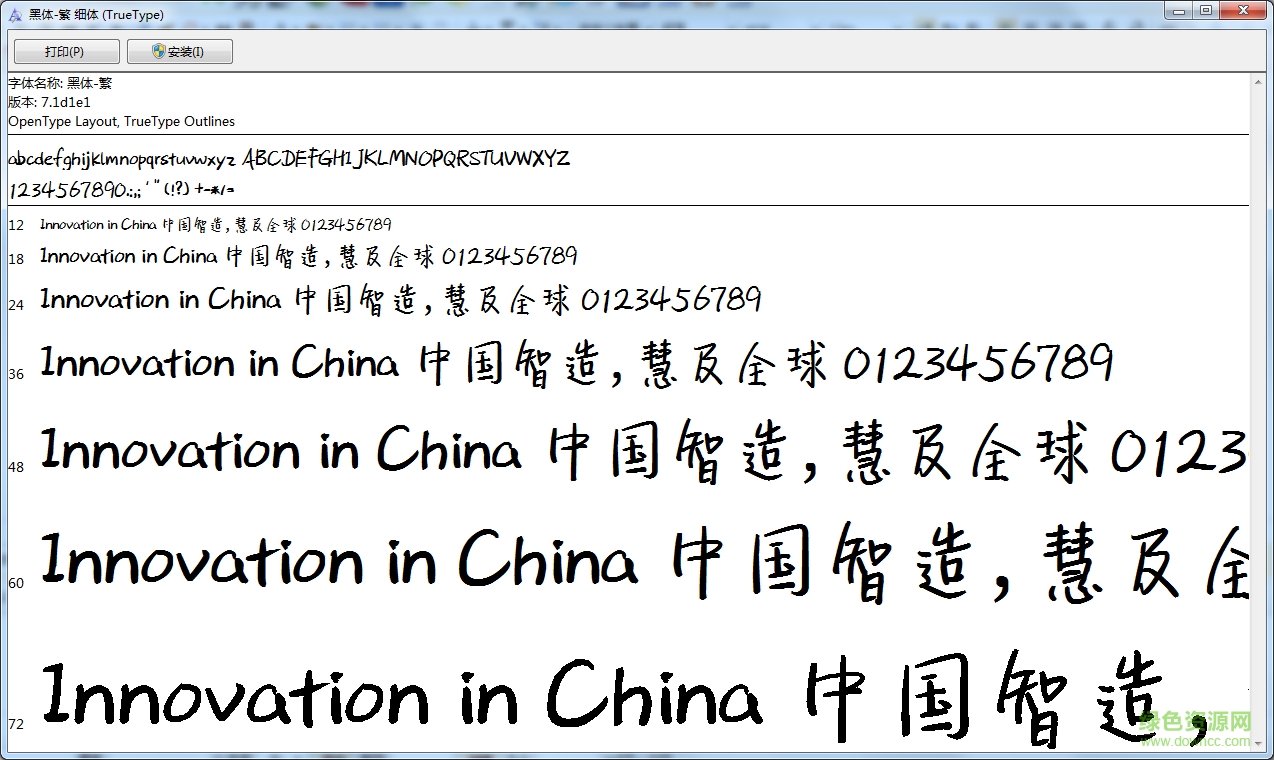
軟件介紹 軟件標(biāo)簽: 新蒂下午茶加粗版 新蒂下午茶 新蒂下午茶加粗版是一款非常可愛的字體,在原有的字體上進(jìn)行了加粗處理,讓字體更加的鮮明醒目,一眼就能看見,非常適合進(jìn)行廣告使用,喜愛的朋友趕快到綠色資源網(wǎng)下載體驗吧!使用方法1.控制面板/字體/文件/安裝新字體。windows xp下找到"控制面板 - 外觀 - 字體",粘貼字體文件即可;vista/7等系統(tǒng)右鍵安裝即可2.直接將字體復(fù)制到C:\WINDOWS\Fonts。 版權(quán)原因,已下架 軟件截圖 上一張下一張(1 / 1) 安裝詳細(xì)截圖 猜你喜歡 新蒂字體 新蒂字體 新蒂字體是比較受用戶喜愛的字體應(yīng)用!包含風(fēng)格華美的剪紙體,美觀大方的黑板報體、活波生動的小丸子體等,每一種字體都擁有不同的風(fēng)格特點。這套字體可以使用用設(shè)計、印刷等行業(yè),同時兼容Windows、mac電腦系統(tǒng)! 查看更多>> 漢儀新蒂日記體字體 3.37M/中文/6.6/官方版下載 漢儀新蒂糖果體 4.54M/中文/5.0/官方版下載 漢儀新蒂小丸子高級字體 3.29M/中文/5.0/v1.00 免費版下載 漢儀新蒂永樂大典體免費版 5.79M/中文/8.3/v1.0 試用版下載 漢儀新蒂手札體字體 10.00M/中文/5.0/下載 新蒂繁星下午茶 5.16M/中文/5.0/下載 其他版本下載 標(biāo)題 大小 更新日期 下載 下載地址 電腦版 點擊報錯 軟件無法下載或下載后無法使用,請點擊報錯,謝謝! 關(guān)閉報錯反饋 請描述您所遇到的錯誤,我們將盡快予以修正,謝謝! *必填項,請輸入內(nèi)容 本類最新 未來熒黑字體 免費版 斗魚追光體字體 v2.0 免費商用版 貓啃網(wǎng)故障黑字體 免費商用版 白無??煽勺煮w 商用免費版 小米miui13系統(tǒng)misans字體 官方最新版 思源真黑體字體(21款) 免費版 用戶評論 熱門評論 最新評論 發(fā)表評論 查看所有評論(0) 昵稱: 請不要評論無意義或臟話,我們所有評論會有人工審核. 字?jǐn)?shù): 0/500 (您的評論需要經(jīng)過審核才能顯示)